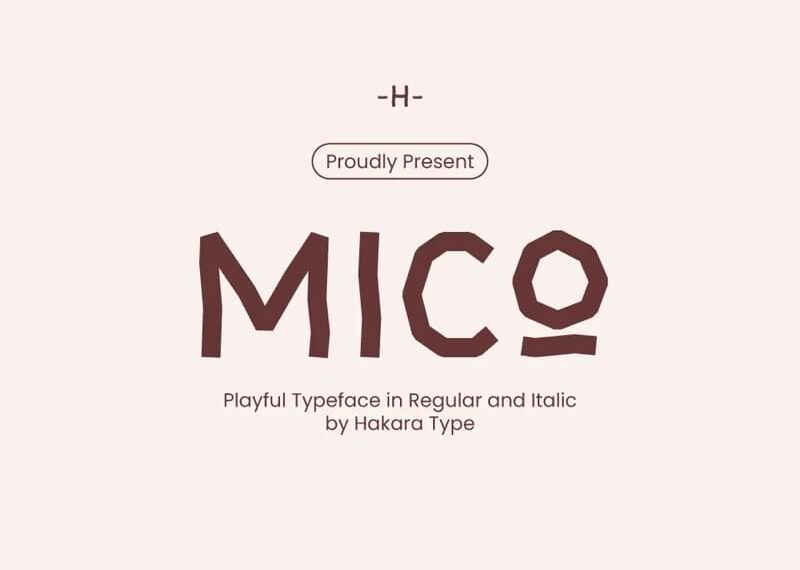
Mico: Free Playful Font Ideal for Branding
Mico: Freier verspielter Font, ideal für das Branding
Mico ist eine spaßige Schriftart, die von Hakara Type erstellt wurde und hervorragend für die Erstellung von Marken und Logos geeignet ist. Sie enthält Groß- und Kleinbuchstaben, Zahlen, Funktionen, Ligaturen und unterstützt mehrere Sprachen. Die Schriftart ist in OTF, TTF und WOFF-Formaten verfügbar und kann persönlich kostenlos heruntergeladen werden, während andere Verwendungen möglicherweise eine Lizenz erfordern.Beispiel für Produktverpackung Ein weiteres Beispiel für Produktverpackung Zeichenliste